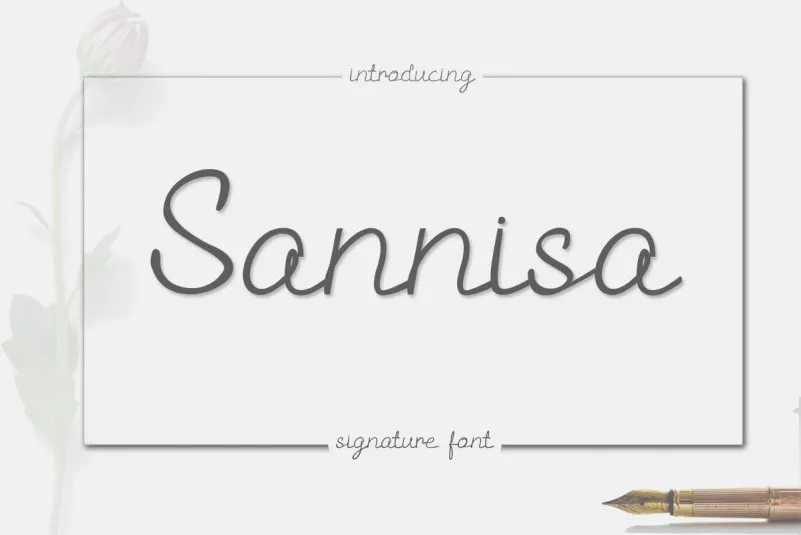
Sannisa Script Font – Fonte Grátis
Sannisa Script Font
A fonte Sannisa Script é inspirada em uma simples script de autografo, oferecendo flexibilidade para diversas aplicações, desde a letra de fonte até materiais de publicação como panfletos e postais. Suave e elegante, ela atende perfeitamente à necessidade de criar um estilo de marca unificado para produtos ou ao fornecer uma atmosfera acolhedora em anúncios, brochuras, cartazes e revistas diárias. Sannisa é a fonte ideal para dar vida aos materiais gráficos, garantindo um toque autêntico que se destaca em qualquer aplicação onde você desejá-la. Como uma escolha segura de design com uma versão escrita à mão, ela traz sofisticação e personalidade ao seu trabalho visual.